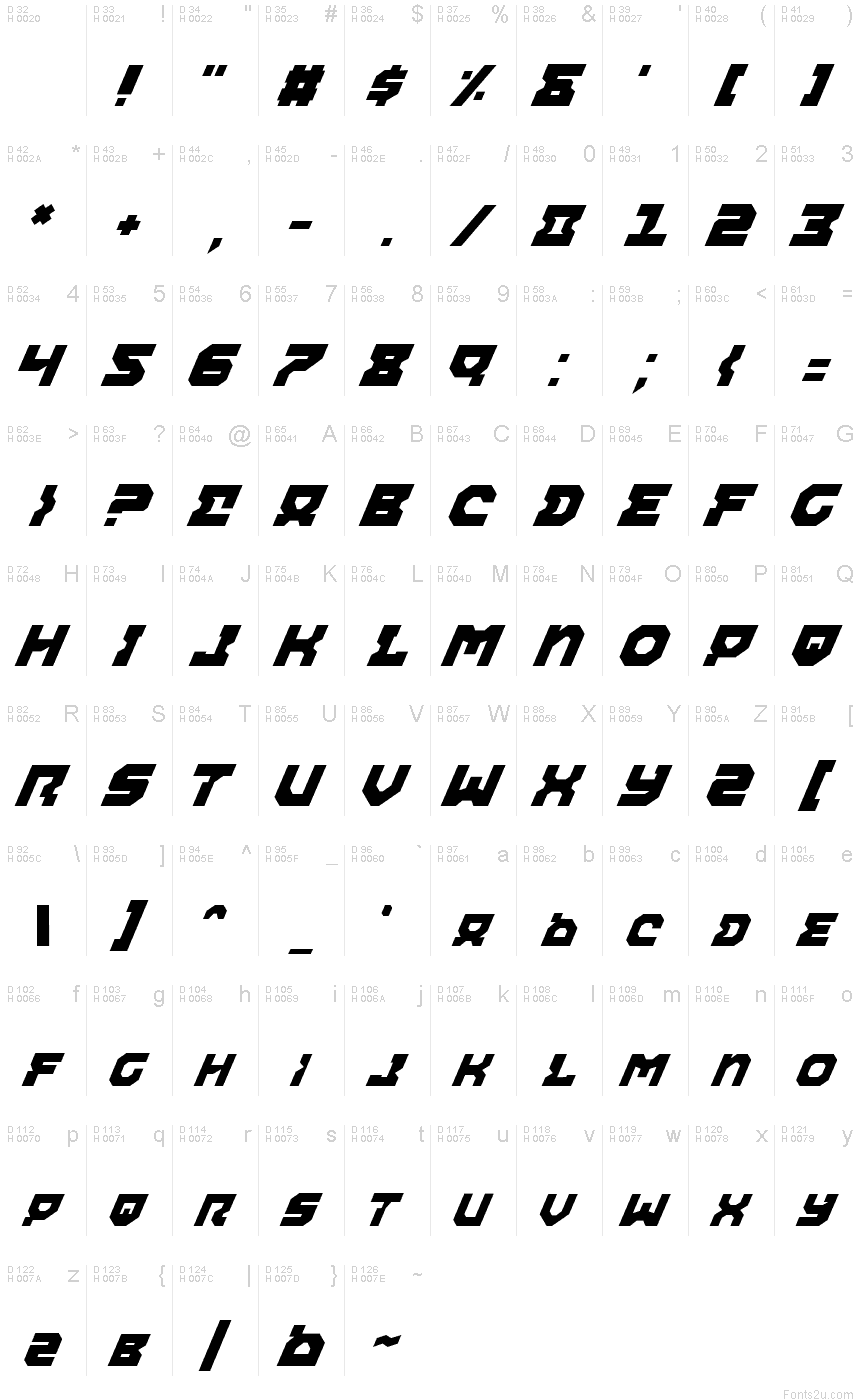
Airacobra Italic
يُعد خط Airacobra Italic من Iconian Fonts خطاً مجانياً من فئة الخطوط التقنية العريضة (Display)، حيث يضرب بقوة تشبه اندفاع محركات الطائرات النفاثة. صُممت كل حرف ليعكس الحركة، مع حواف حادة ومنحوتة وميلان أمامي مدمج يجعل الكلمات القصيرة تبدو وكأنها تتجاوز حدود السرعة. تتميز الأشكال بالبنية المربعة والمدمجة مع الحفاظ على النقاء، مما يمنح العناوين طاقة ميكانيكية كثيفة تظهر بوضوح وسرعة سواء على الشاشة أو في المطبوعات.
باستخدام Airacobra Italic، يمكنك ضخ سرعة فورية في تصميمات العلامات التجارية للرياضات الإلكترونية، وملصقات سباقات السيارات، وأغلفة أفلام الخيال العلمي، وعناوين أفلام الأكشن، والشعارات التقنية، أو الصور المصغرة الجذابة على يوتيوب. يتألق هذا الخط المجاني خاصة عند استخدامه بأحجام كبيرة، حيث تبرز زواياه القاطعة ووقفته المائلة بقوة، كما أنه يتناسب بشكل جيد مع خط sans serif هندسي بسيط للنص الأساسي، مما يحافظ على وضوح تصميمك بينما يقوم العنوان بالجزء الأكبر من العمل البصري.